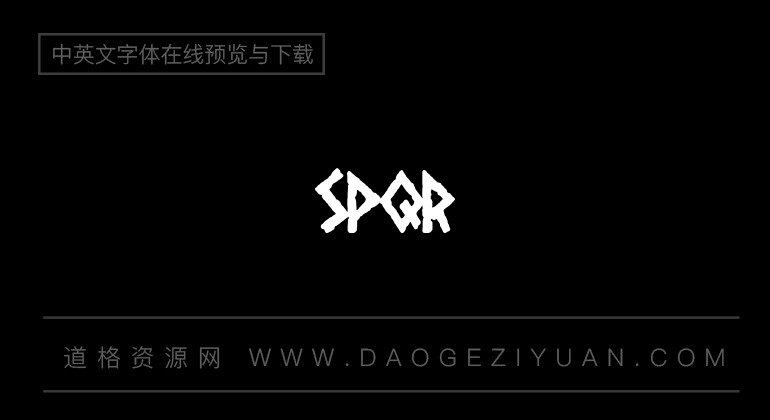
SPQR是一种字体,它由设计师Carlo Olsson于2013年创造。它的设计灵感来自古罗马的铭文和雕刻。SPQR是古罗马的缩写,意思是"Senatus Populusque Romanus",意为"罗马参议院和人民"。这个缩写在古罗马时期经常出现在公共建筑和纪念碑上,现在它也被用作罗马市的标志。 SPQR字体的特点是它的线条粗细变化很大,有时候甚至会出现断点,呈现出古罗马时期铭文的效果。它的字形也比较典雅,适合用于设计和排版。此外,SPQR字体也支持多种语言,包括英语、西班牙语、葡萄牙语、法语、德语、意大利语等。内容介绍
SPQR是一款非常不错的手写艺术字体,具有很好的视觉感,适合于文化类的宣传设计、商业类品牌的广告和产品包装设计以及个性化文字排版等较多场景。